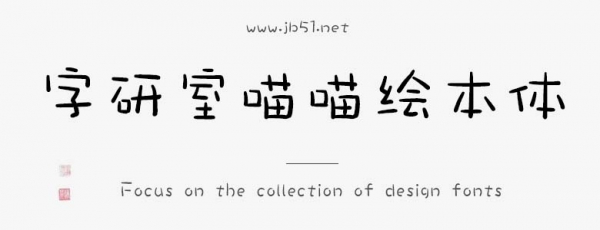
字研室喵喵繪本體是字研室出品的藝術(shù)字體,字體筆觸略細(xì),字形略顯童趣可愛(ài),具有很好的視覺(jué)感,適合應(yīng)用于藝術(shù)設(shè)計(jì)、平面宣傳設(shè)計(jì)、網(wǎng)頁(yè)設(shè)計(jì),書(shū)法字帖等領(lǐng)域。有需要的朋友快來(lái)本站下載使用吧。